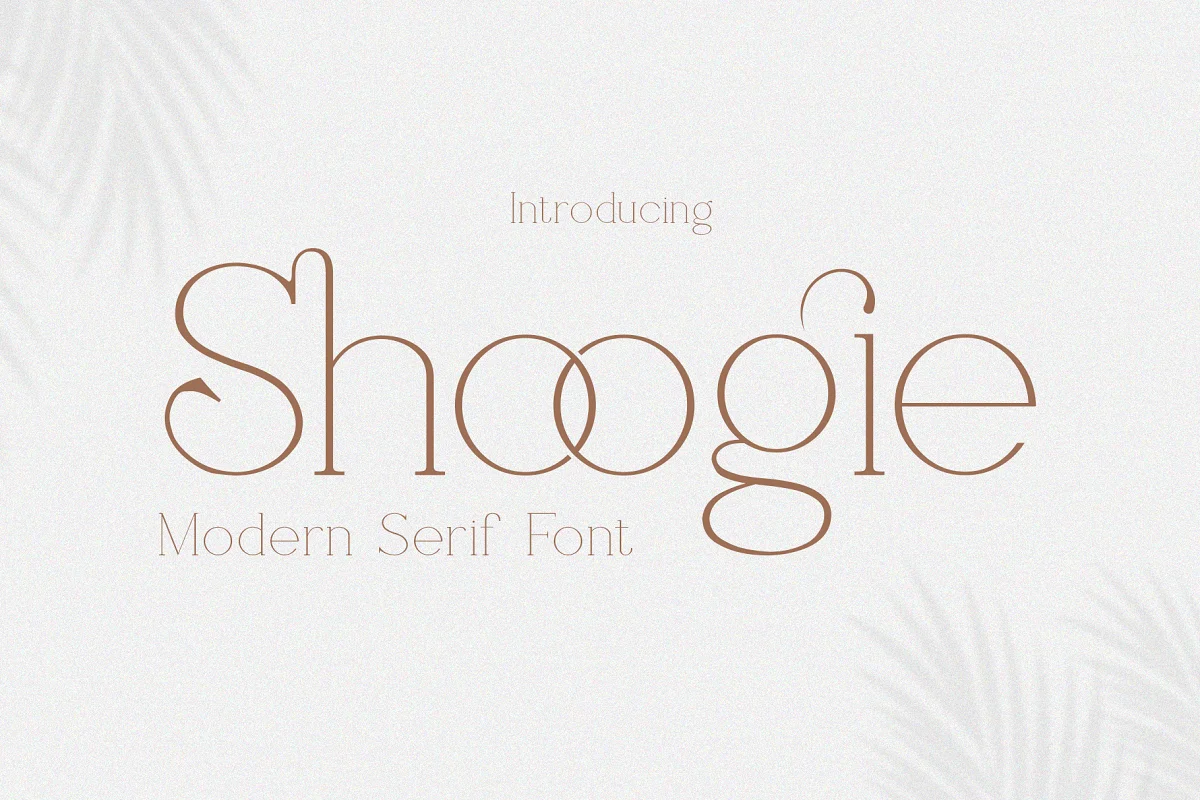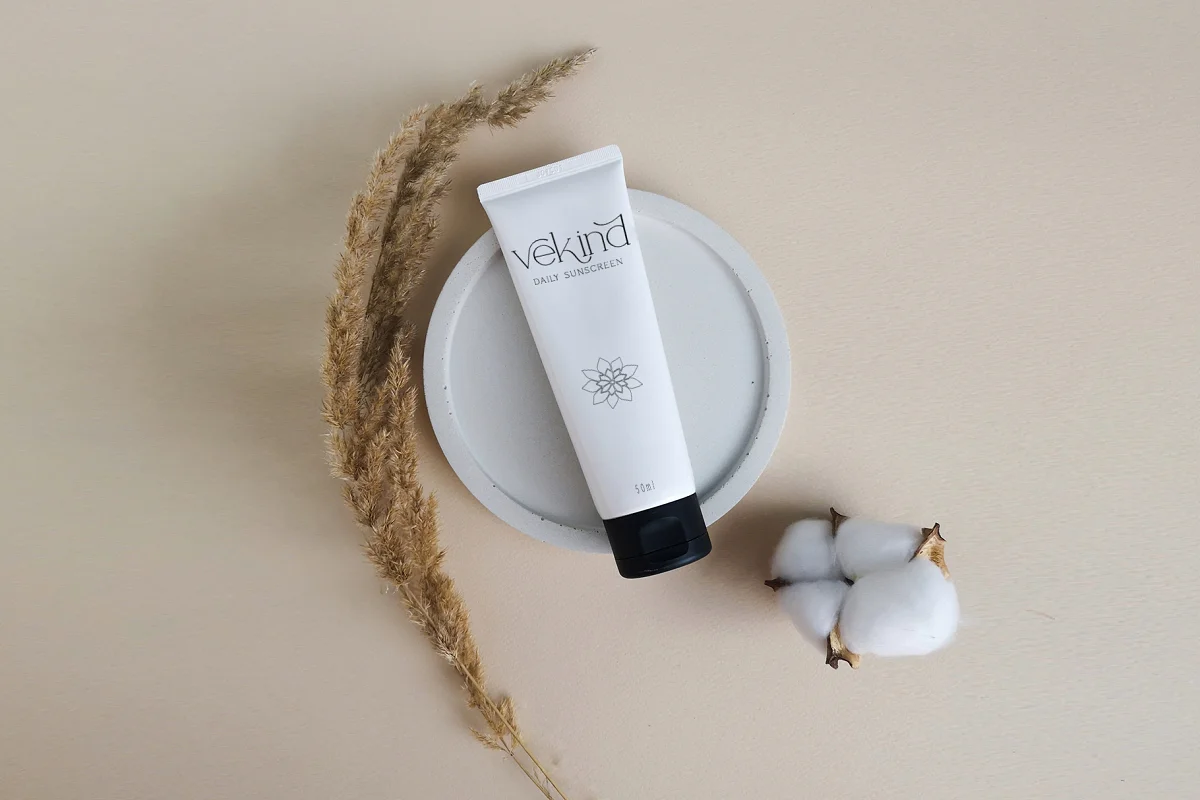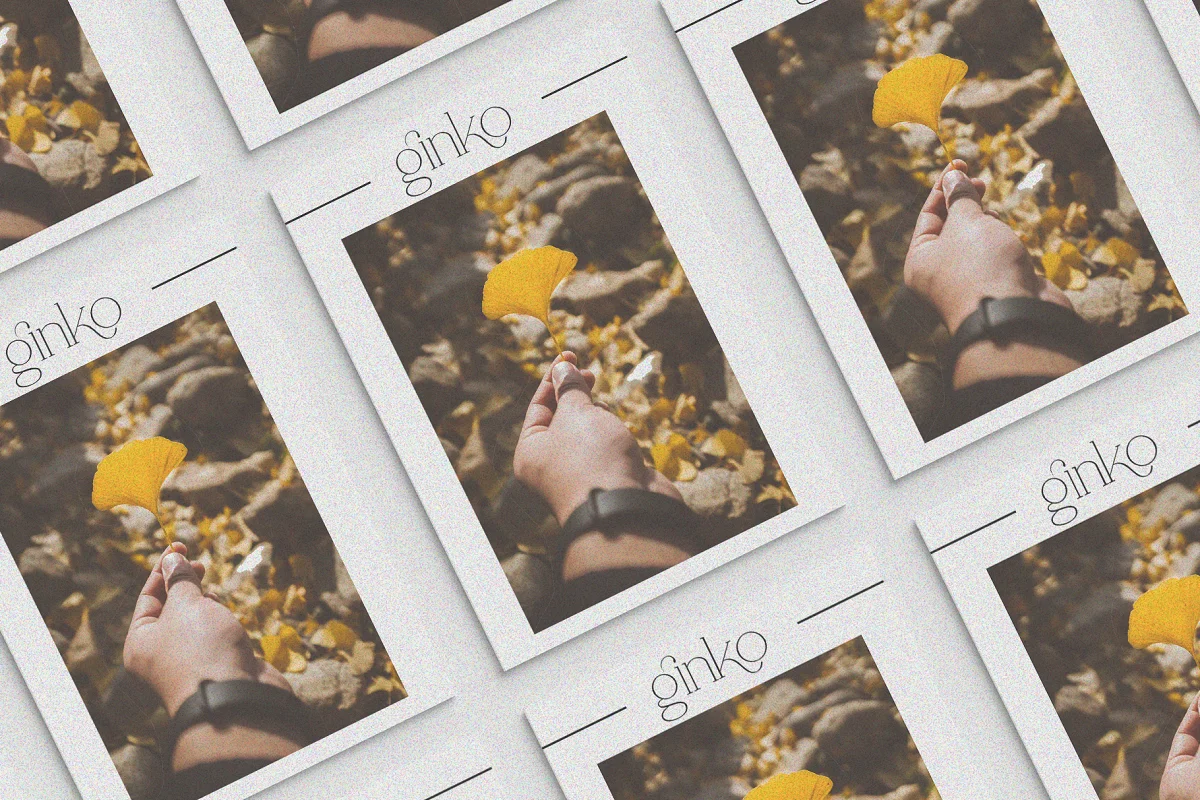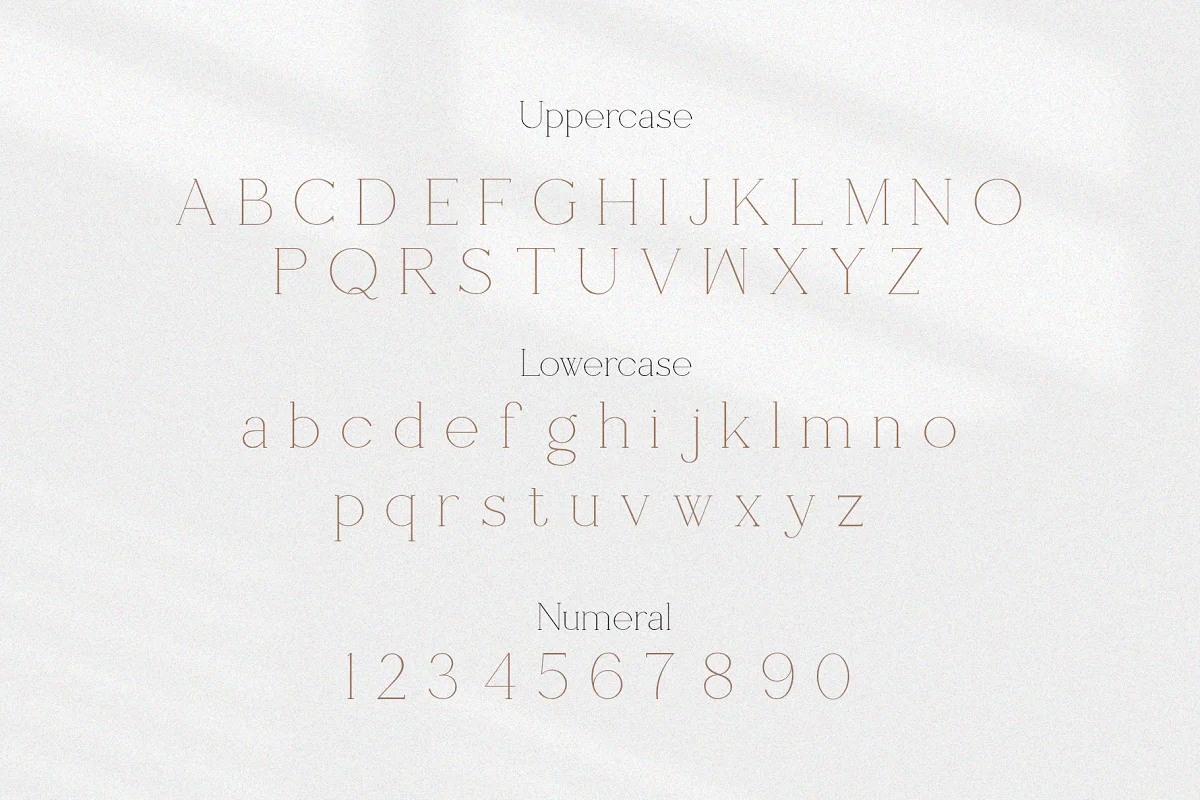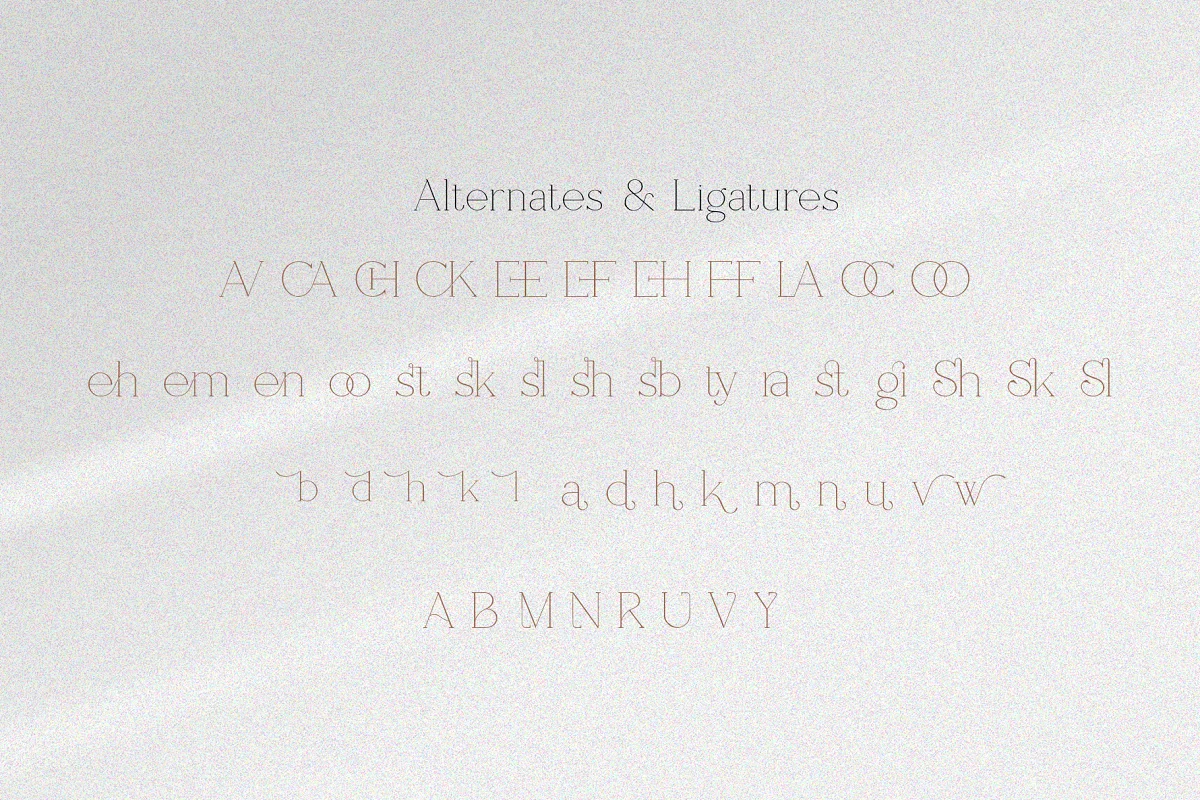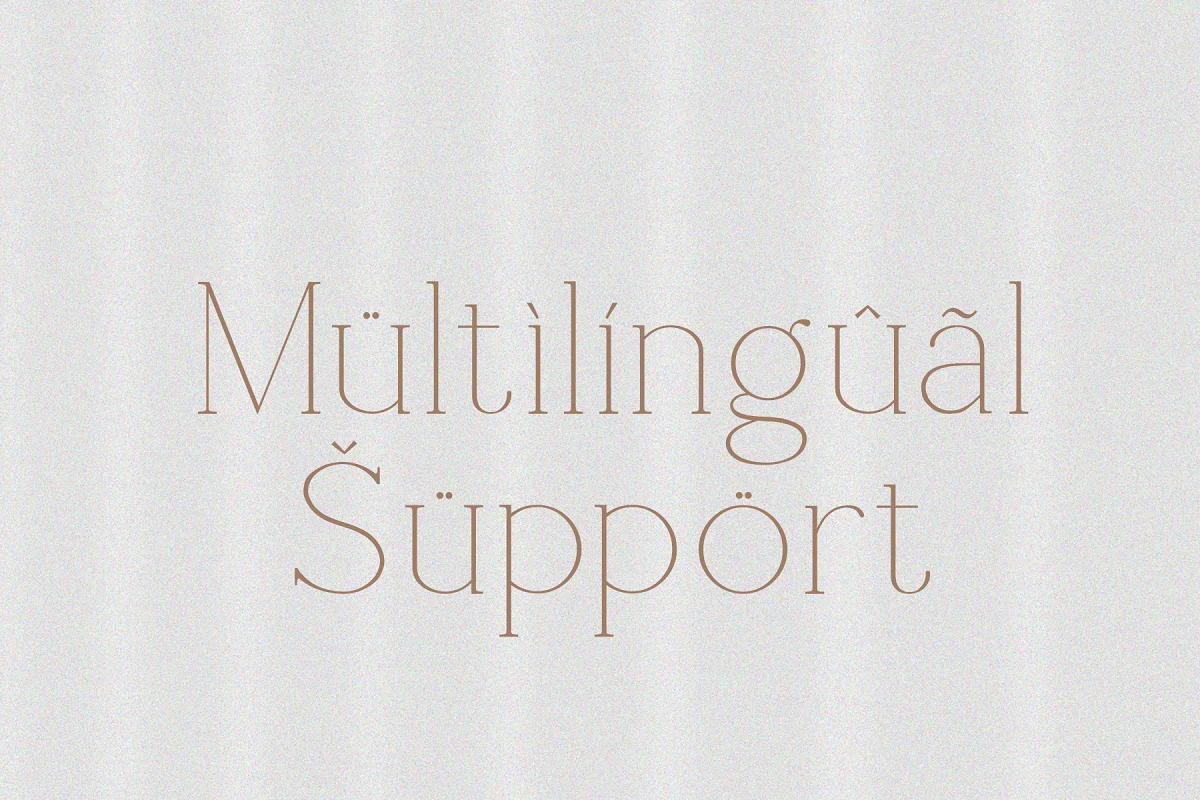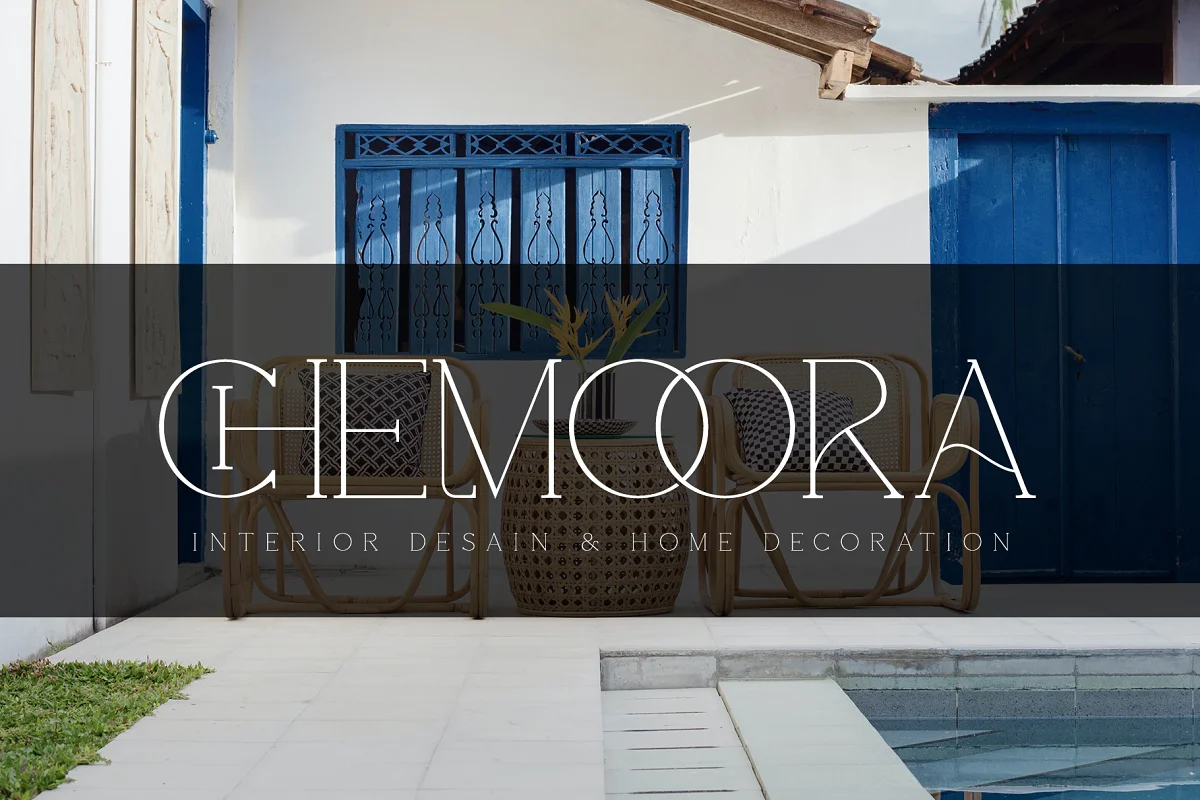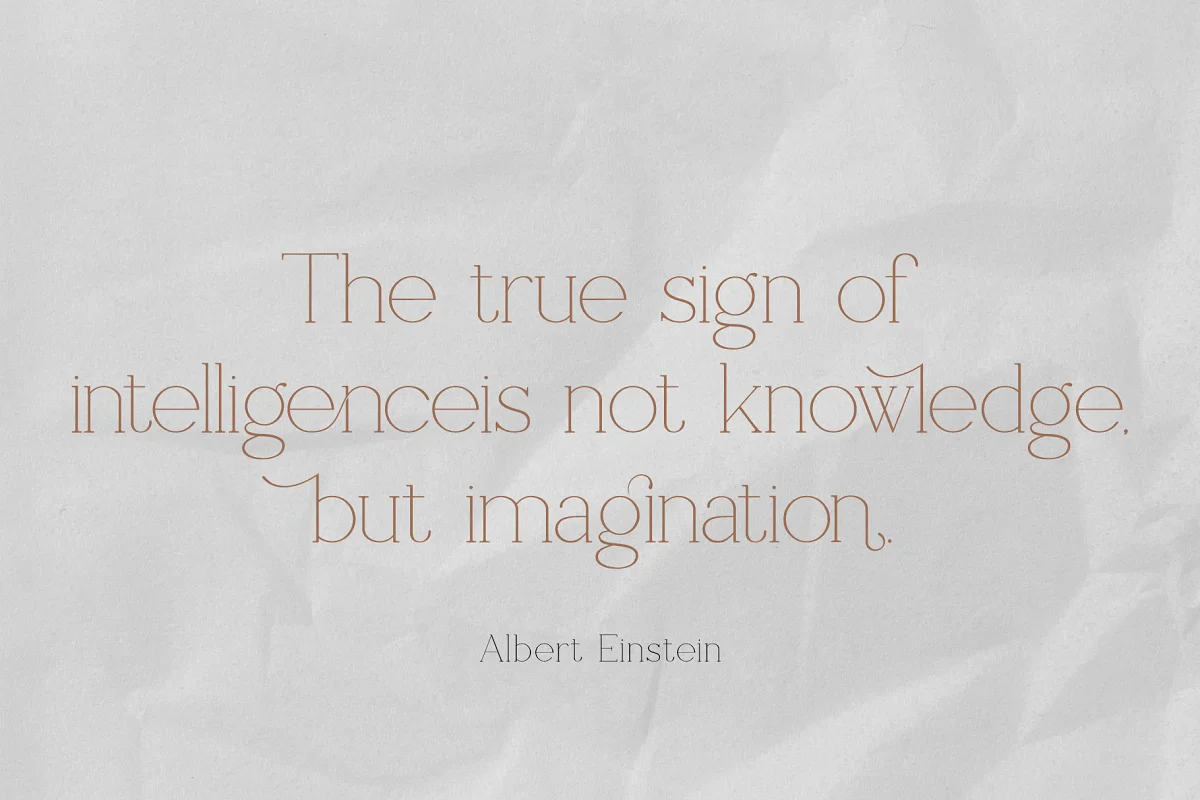
Shoogie Serif là phông chữ serif cân bằng, mượt mà, thanh lịch và đầy phong cách. Anh ấy có một nhân vật đẹp. Nó hoàn toàn phù hợp với các thiết kế thiệp mời, logo công ty, tên phim, danh thiếp, tên sách, tên thương hiệu và nhiều thiết kế khác. Shoogie Serif là một phông chữ serif tinh tế toát lên sự tinh tế và sang trọng. Sự xen kẽ và chữ ghép đầy phong cách của nó làm cho phông chữ này trở thành đối tác hoàn hảo cho bất kỳ dự án nào.
- Dây chằng
- Chữ hoa và chữ thường
- Đánh số và chấm câu